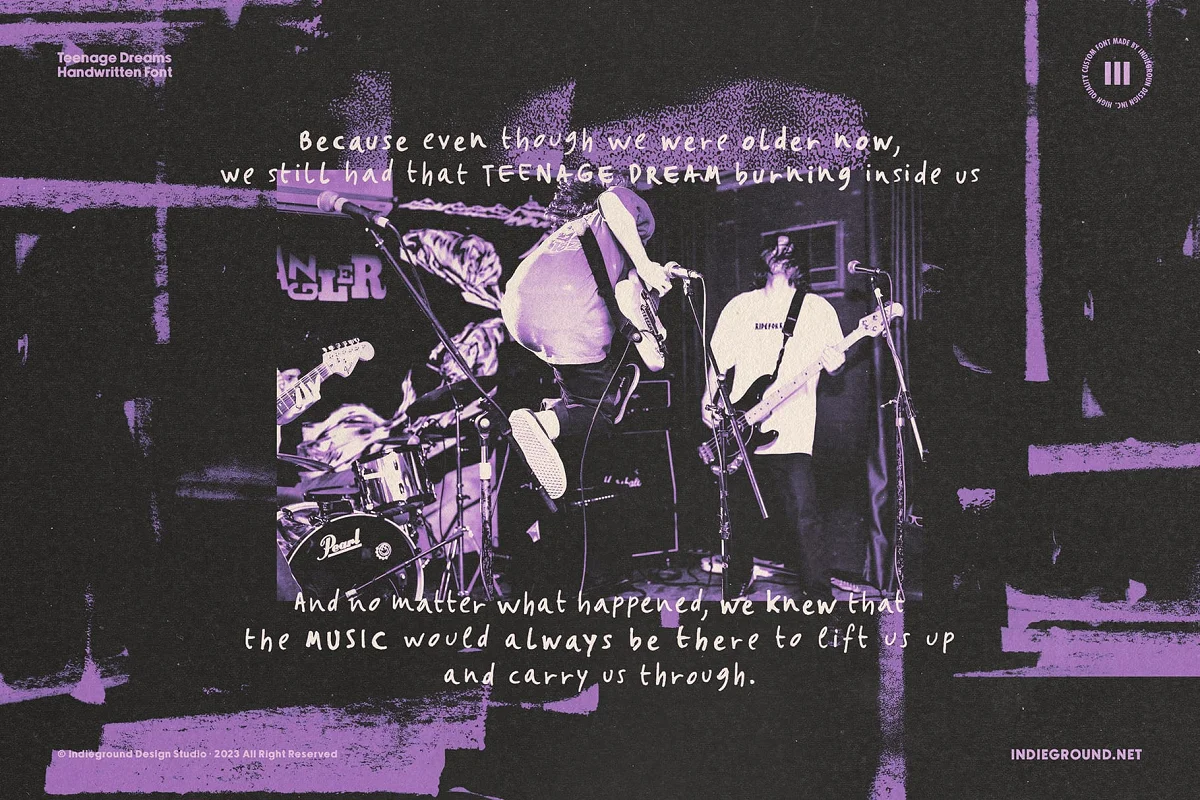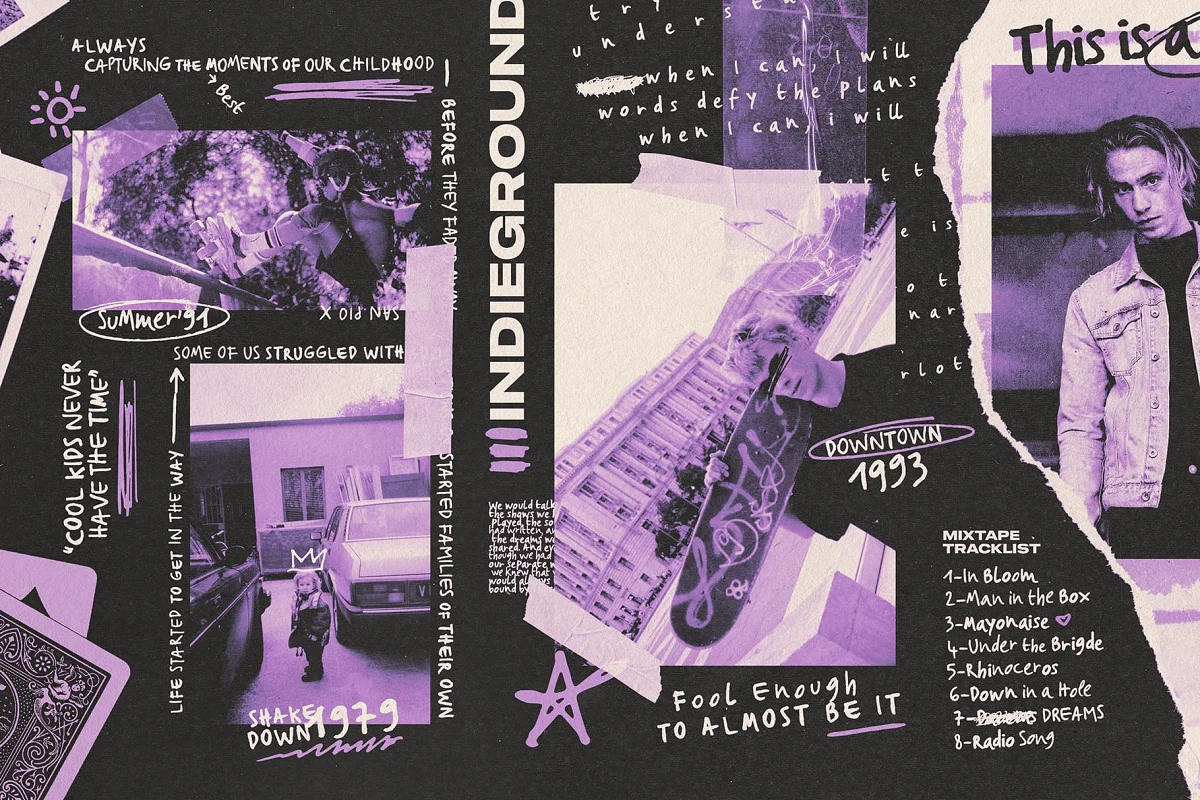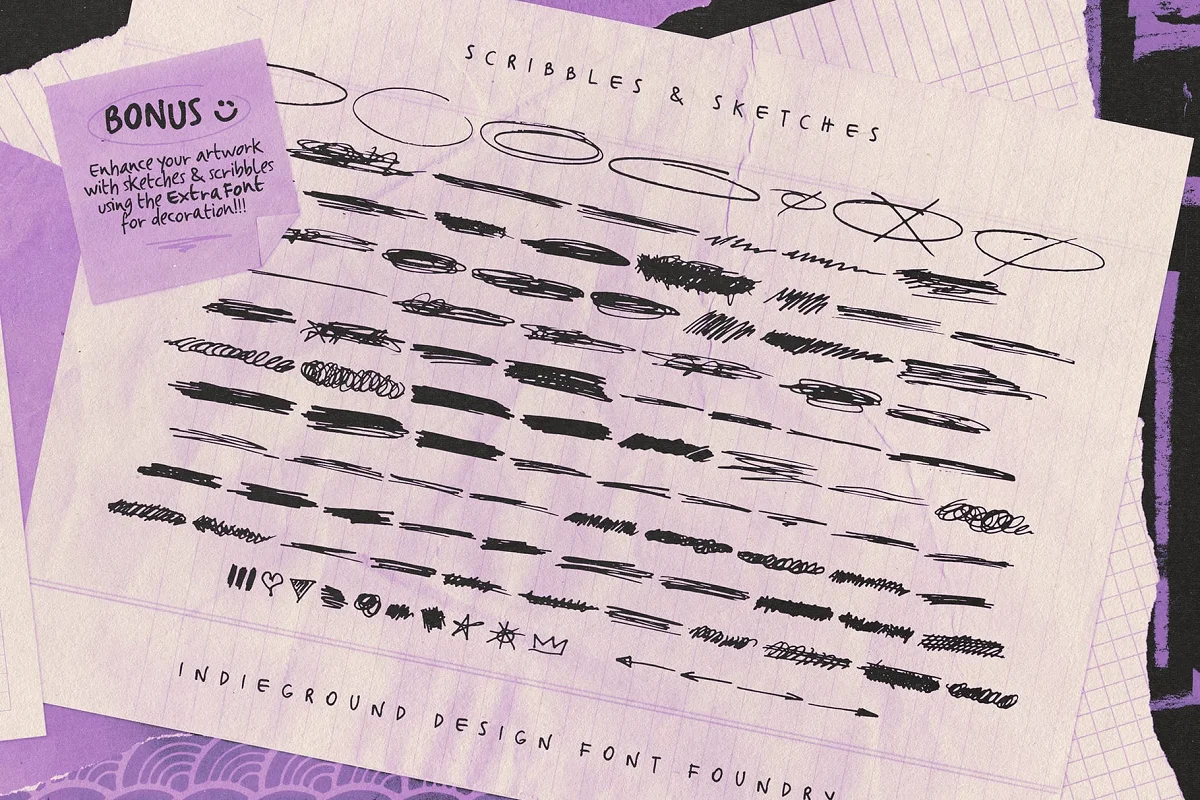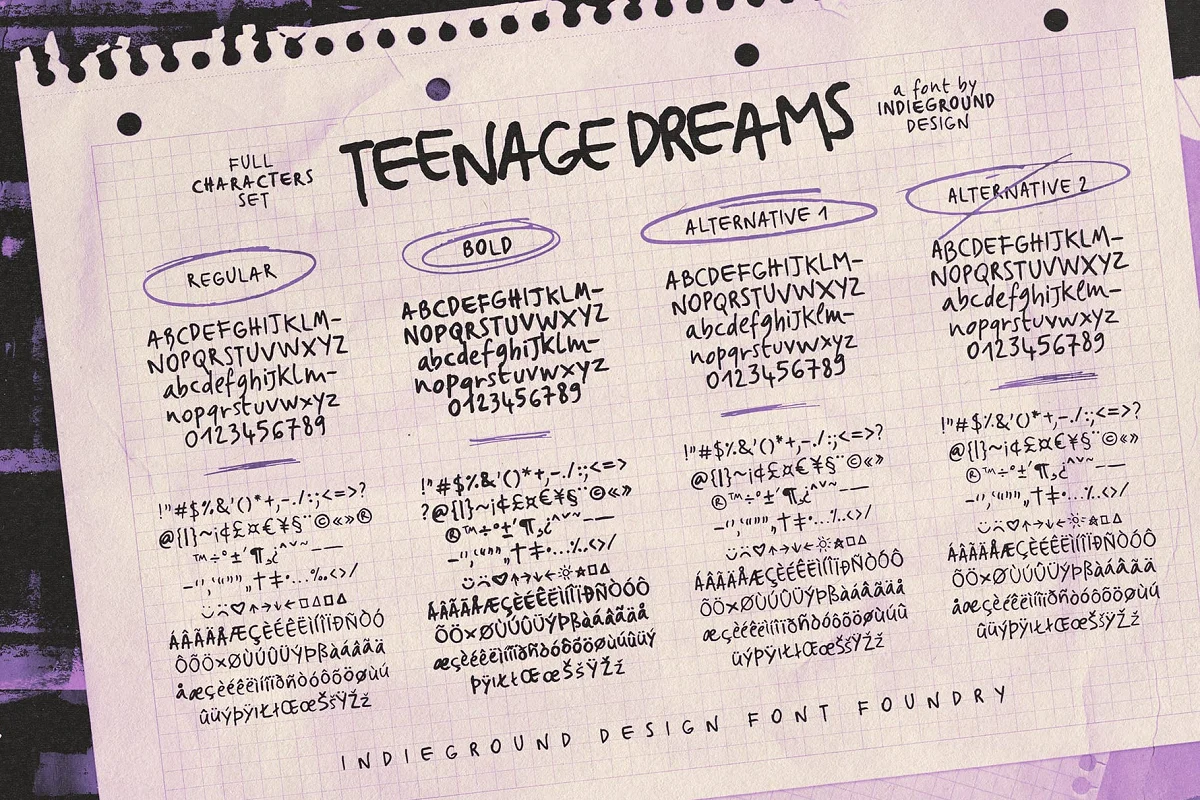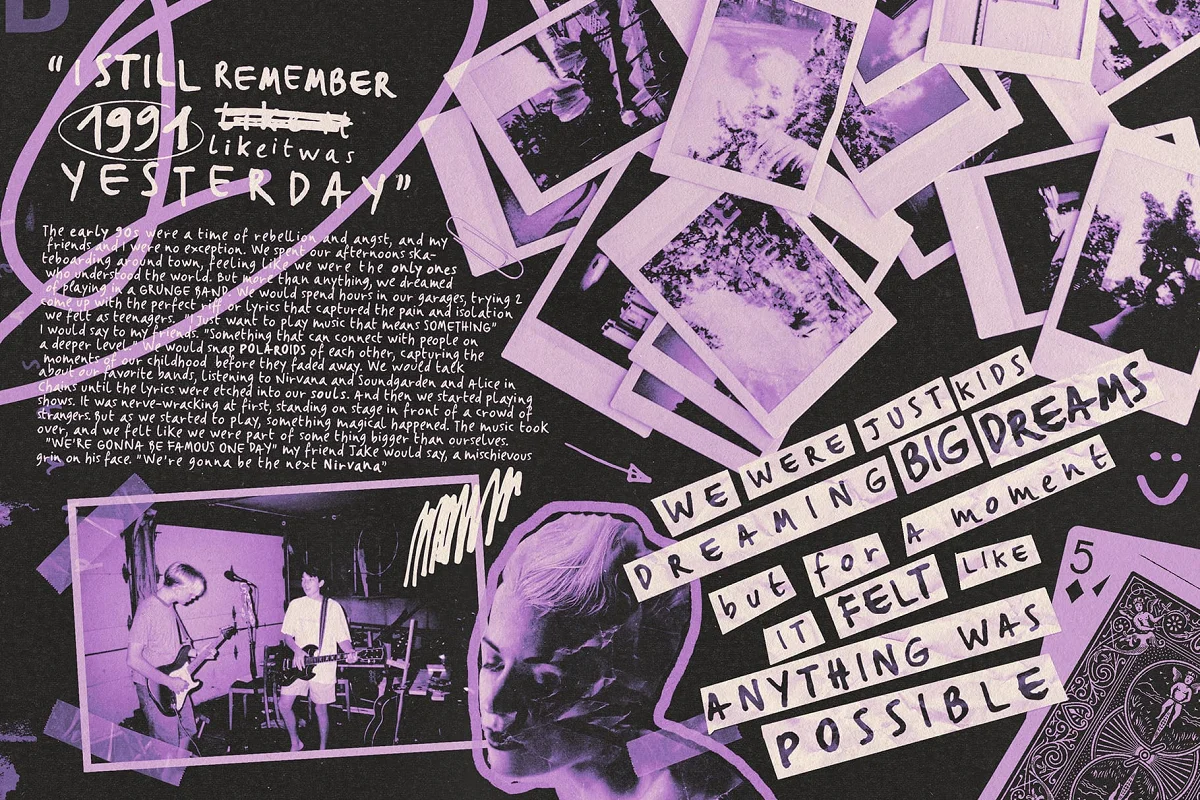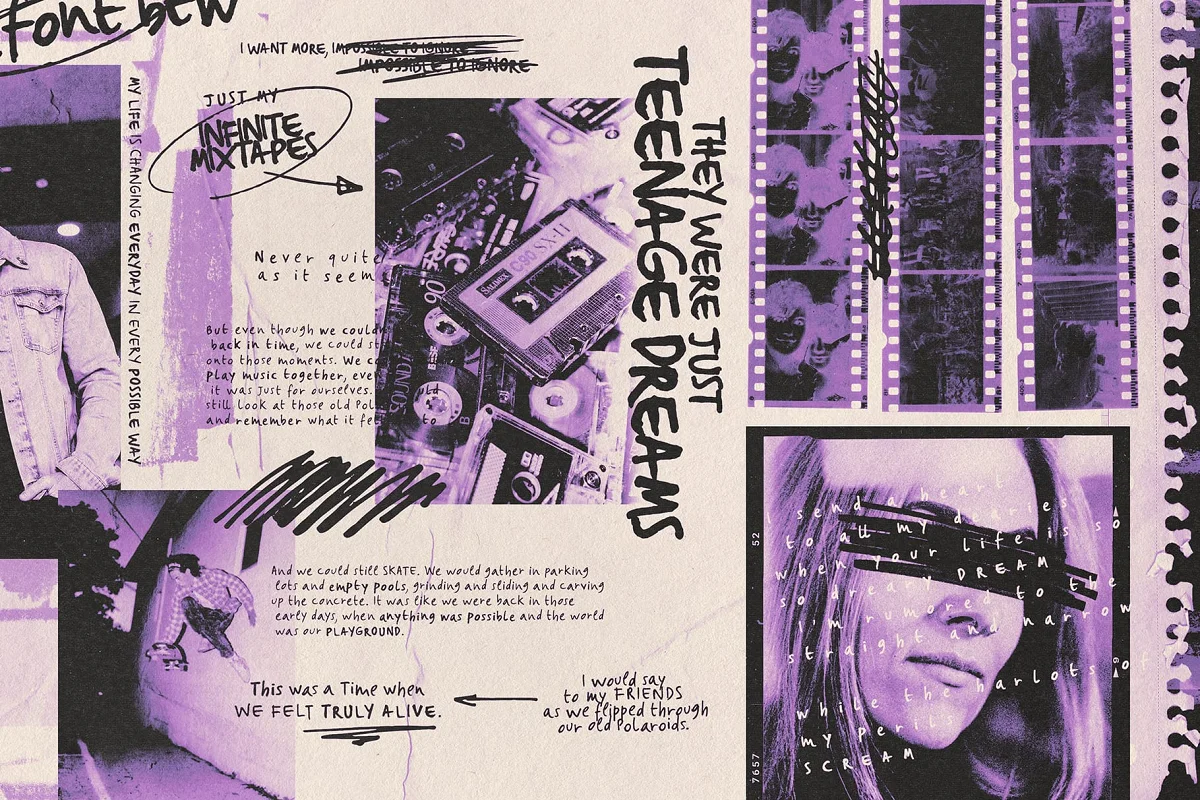
Teenage Dreams Font của Indieground là một kiểu chữ viết tay lý tưởng để mang lại không khí hoài niệm của thập kỷ 90. Với tính chất độc lập của nó, kiểu chữ grungy này sẽ thêm một chút tự spontaneity và phong cách cho bất kỳ dự án sáng tạo nào. Kiểu chữ này tái tạo không khí của những năm thơ ấu của chúng ta trong thập kỷ 90, khi chúng ta nghe nhạc của Smashing Pumpkins, mang giày Chucks và tham gia các buổi biểu diễn indie. Chúng ta thích nghĩ về thời kỳ của sự kỳ diệu, khám phá và tưởng tượng đó, và Teenage Dreams là lựa chọn hoàn hảo để mang lại chúng vào các dự án sáng tạo của chúng ta. Đạt được hiệu ứng viết tay chân thực bằng cách kết hợp 4 phiên bản khác nhau trong các tiêu đề và bìa, tạo ngay lập tức các tác phẩm typographic với thái độ tùy chọn và gần gũi. Hơn nữa, chúng tôi cũng đã thêm một phiên bản thưởng thức thứ 5 của kiểu chữ mộng mơ này, với những đường vẽ và hình vẽ bạn có thể thêm vào thành phẩm của mình. Điều này giúp bạn có được hiệu ứng scrapbook grungy trong khi thêm sức mạnh và phong cách vào bất kỳ dự án nào. Nó tuyệt vời khi sử dụng trên nền tối, nền ồn, hoặc được sử dụng trên ảnh và bức ảnh!